双尖引号
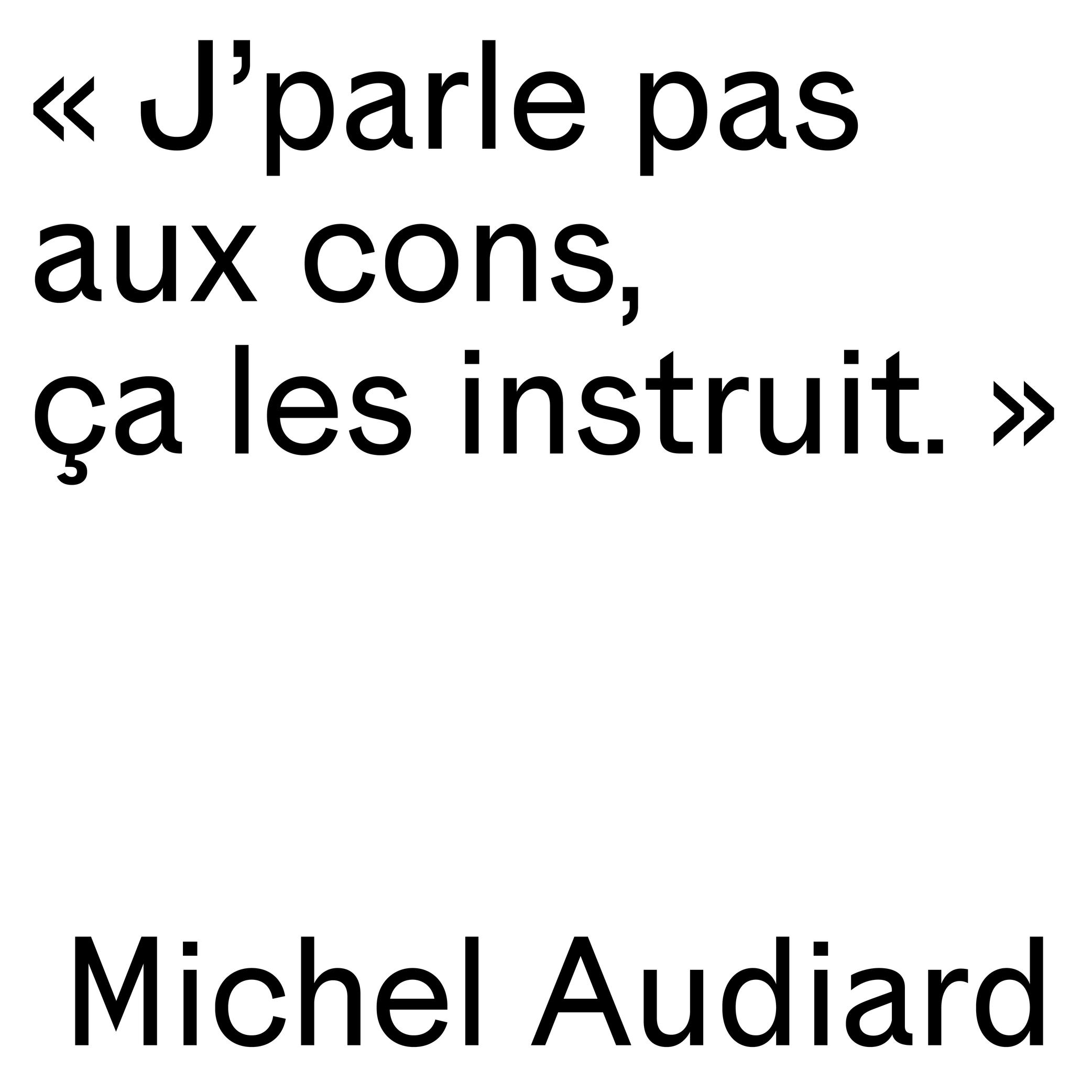
双尖引号 (或楔形引号)是多种欧洲语言(如法语、葡萄牙语和意大利语)中使用的引号。
双尖引号的起源很难追溯,但最早使用双尖引号的书籍之一可追溯到 1527 年荷兰/比利时印刷商胡斯·巴蒂尤斯(Josse Badius)的作品,其中使用了双尖引号。它们可能是法国印刷商和字冲雕刻师纪尧姆·勒·贝(Guillaume Le Bé,1525–1598)发明的,并以他的名字命名:“guillemet” 是 “Guillaume” 的缩写。
双尖引号的形状像两个小箭头,默认位于基线和 x 字高之间,与小写字母对齐。作为区分大小写的备选字符形,它们可以位于基线与大写字母高度之间的中心位置,以便更好地与大写字母对齐。
根据语言的不同,它们向内或者向外指向一段应用的文本;要么是双尖引号,要么是单尖引号(单尖引号用作二级引号);后加空格或不加。这里有一些例子:
« French » 或 ‹ French ›
«Italian»
»Danish«
注意:“像这样” 的逗号状弯引号在英语中才是标准的。
(左指双尖引号)
LEFT-POINTING DOUBLE ANGLE QUOTATION MARK: U+00AB
(右指双尖引号)
RIGHT-POINTING DOUBLE ANGLE QUOTATION MARK: U+00BB
(左指单尖引号)
SINGLE LEFT-POINTING ANGLE QUOTATION MARK: U+2039
(右指单尖引号)
SINGLE RIGHT-POINTING ANGLE QUOTATION MARK: U+203A